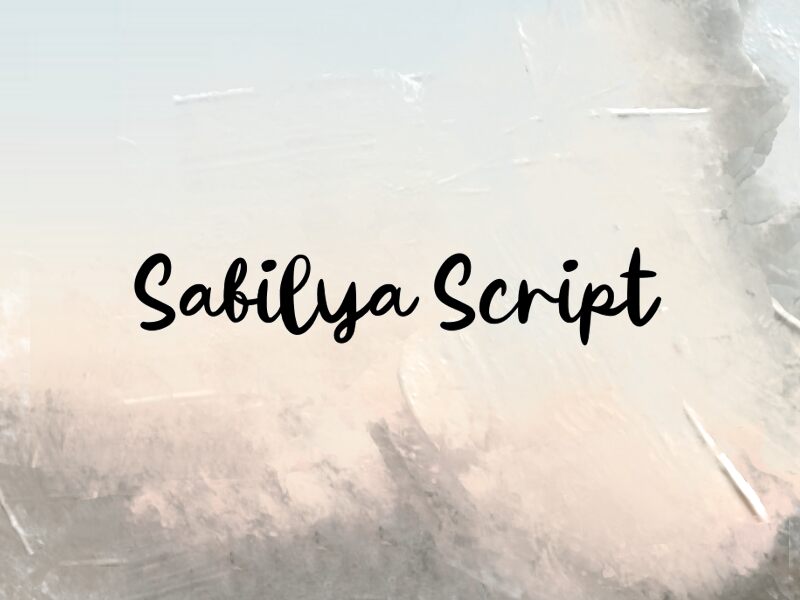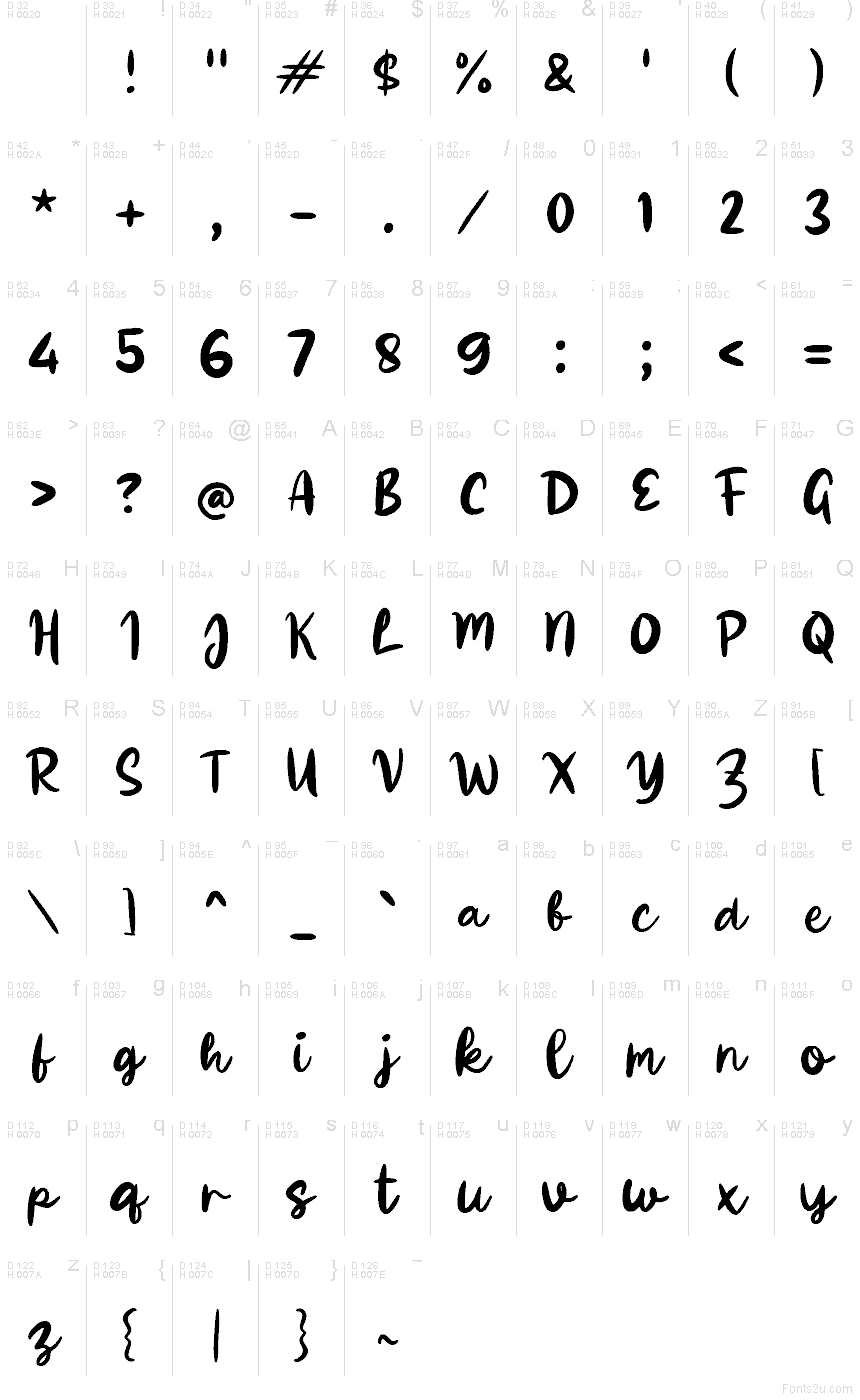
Sabilya Script
Sabilya Script di Wep è un font brush script gratuito con un ritmo di scrittura a mano libera e tratti ampi e decisi. Le lettere oscillano tra forme morbide e arrotondate e ampie curve ascendenti, conferendo un aspetto personale e spontaneo che ricorda più una rapida scritta a pennarello che una calligrafia ricercata.
Si adatta perfettamente al branding di boutique, menu di caffè, biglietti d'auguri, packaging di prodotti beauty e grafiche per citazioni sui social media, dove quel tratto casuale è in grado di sostenere da solo una breve riga di testo. Essendo un font gratuito, funziona bene anche per copertine, titoli e targhette, specialmente quando vuoi che siano le legature fluide e i lunghi riccioli a creare tutto lo stile.